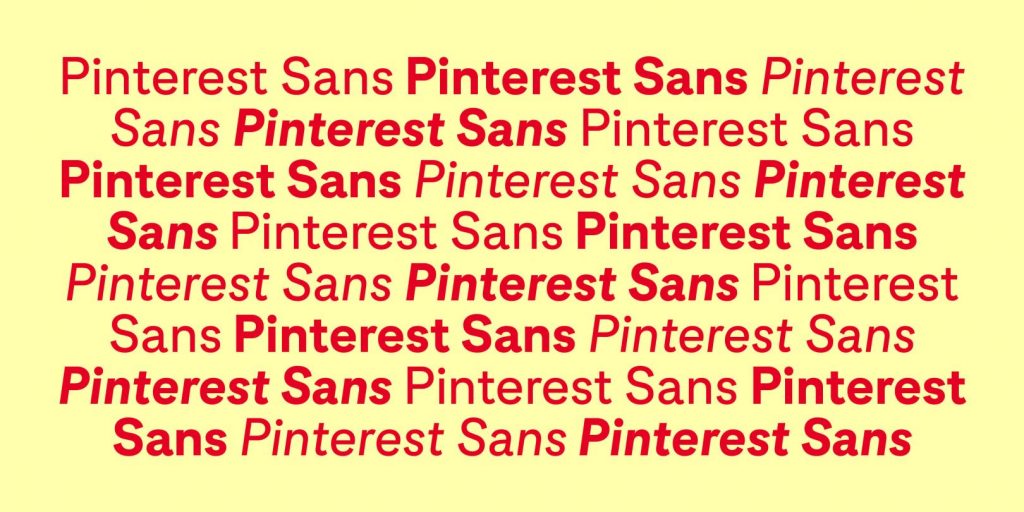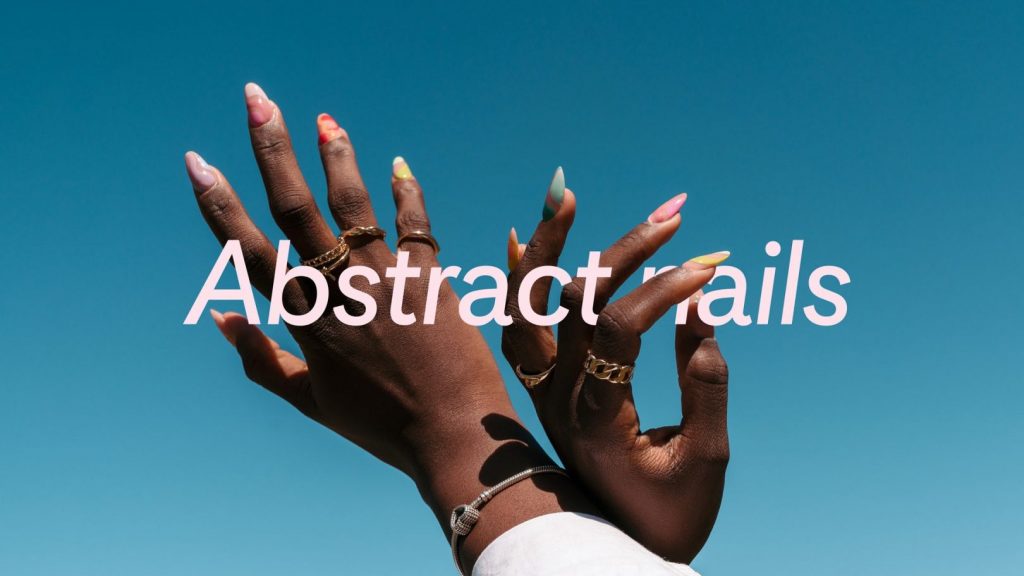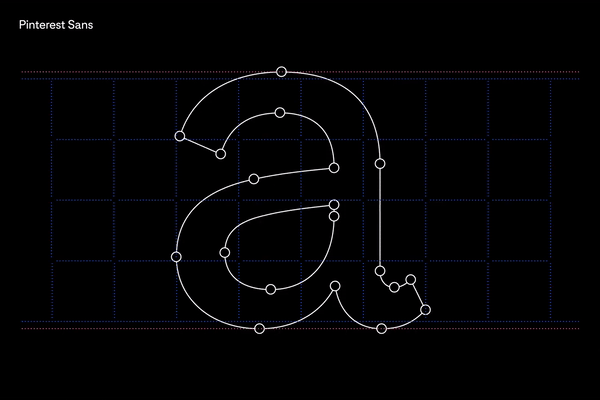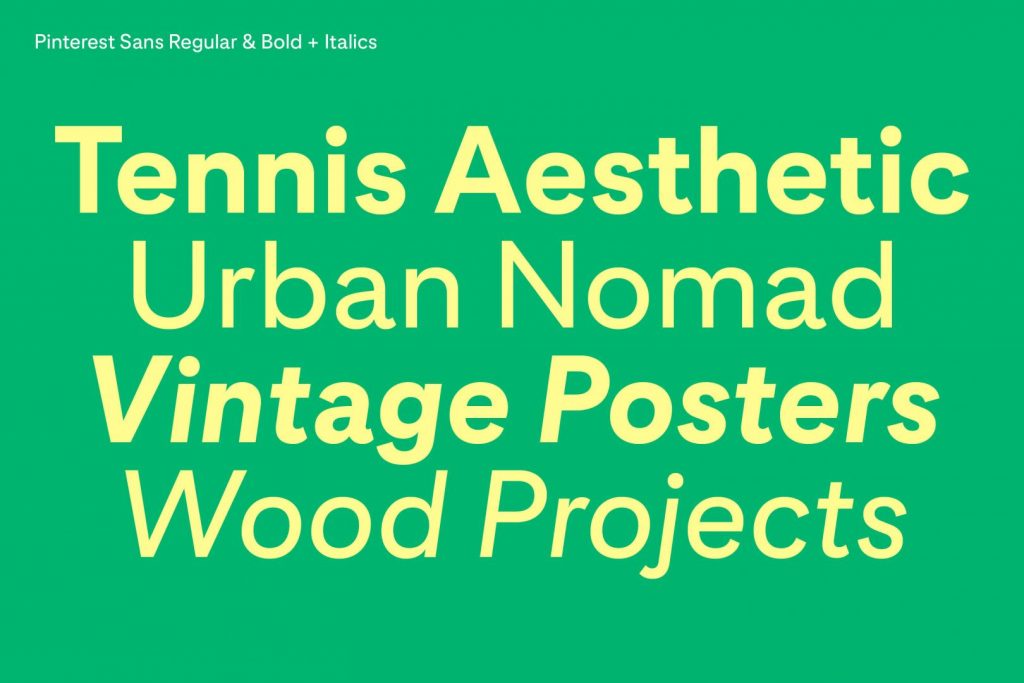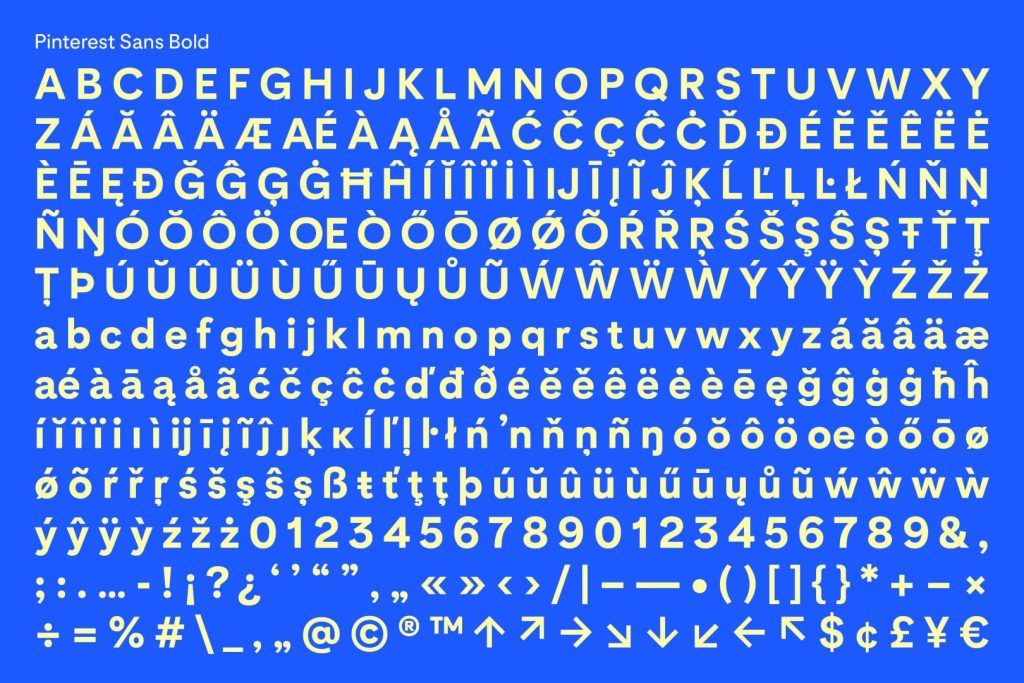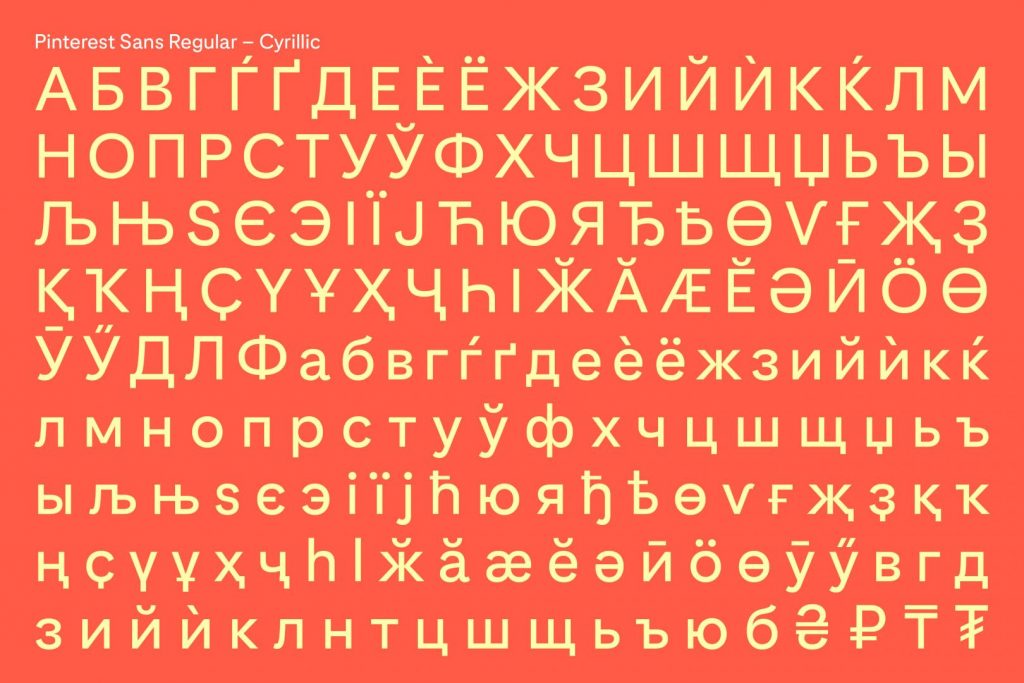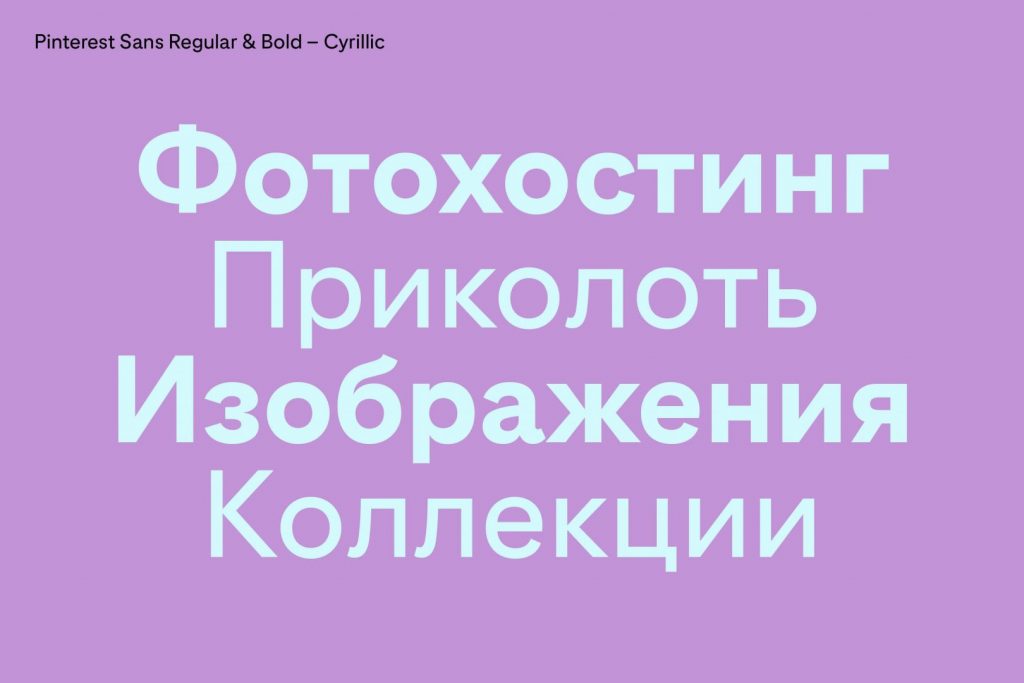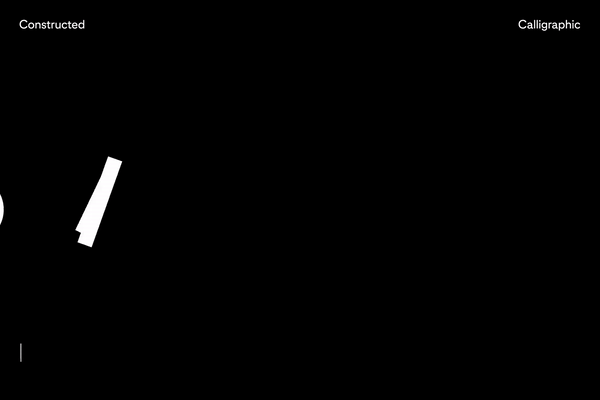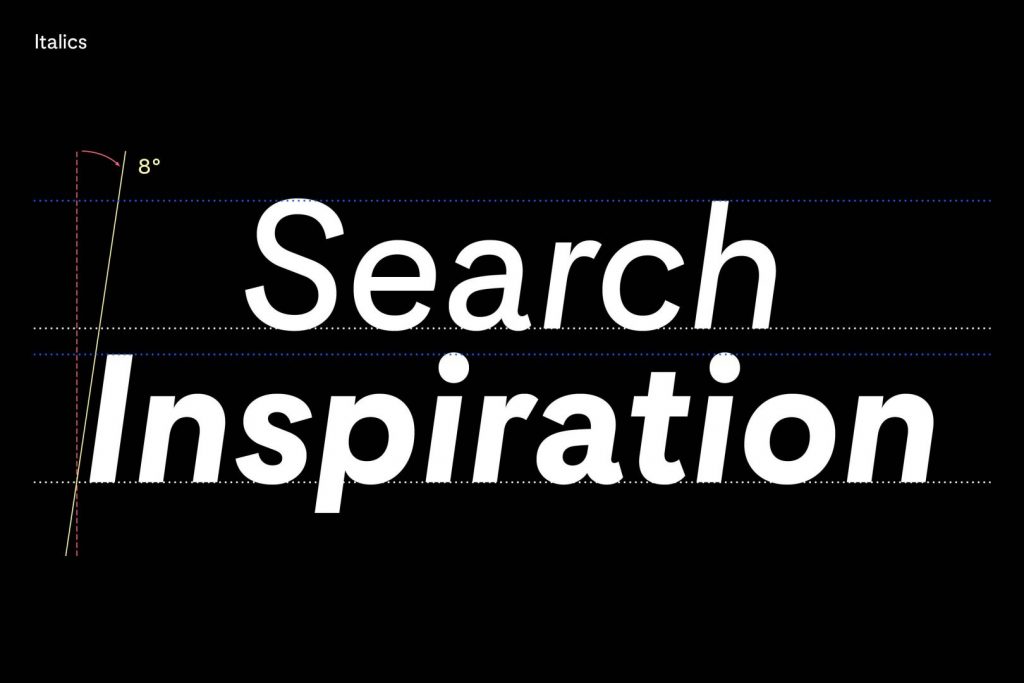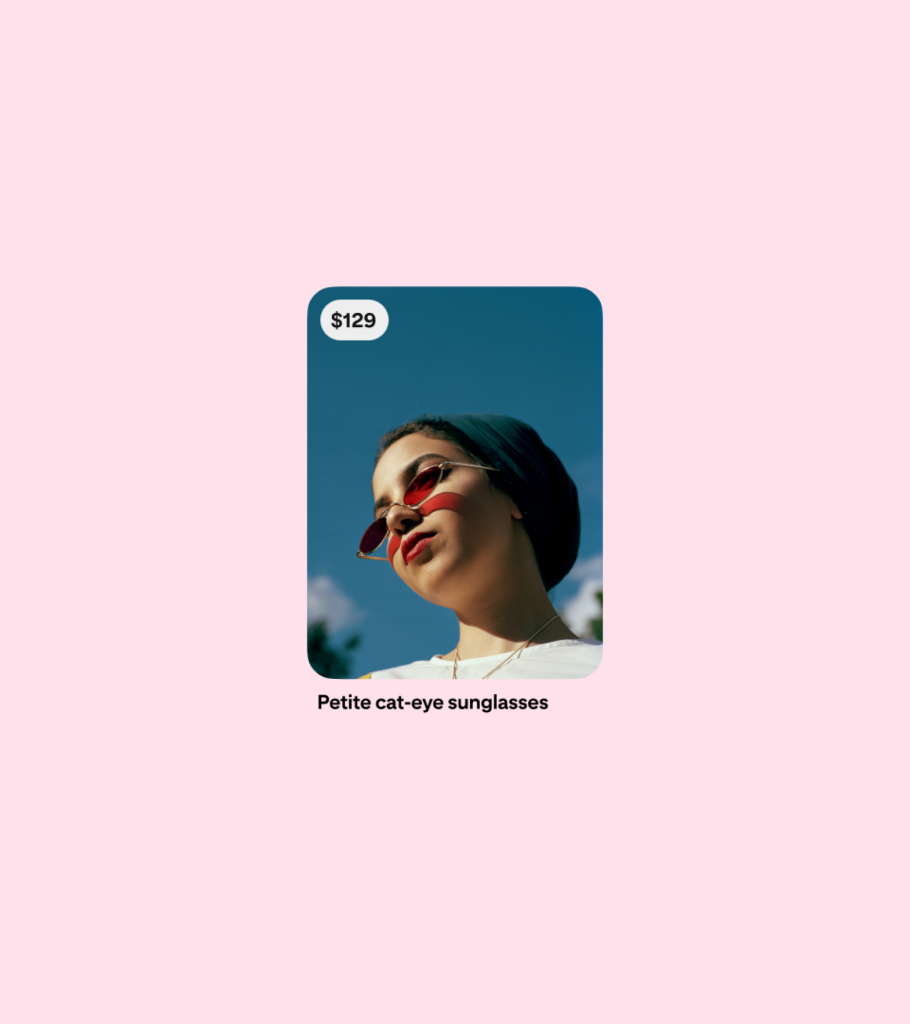
Xưởng thiết kế kiểu chữ nổi tiếng Grilli Type của Thụy Sỹ vừa kết hợp với Pinterest để cho ra đời typeface của bộ font chữ Pinterest Sans, trong kế hoạch hợp nhất thương hiệu trực quan của mạng xã hội hình ảnh này.
Ngoài việc tạo ra Pinterest Sans và Pinterest UI để tăng khả năng đọc cũng như số lượng phong cách riêng của hãng, dự án còn mở rộng để hỗ trợ các kiểu gõ Cyrillic, Hy Lạp, Việt Nam và Nhật Bản.
Trong showcase giới thiệu quá trình thực hiện, Grilli Type cho thấy sự tỉ mỉ đến từng chi tiết một cách đáng kinh ngạc. Pinterest Sans có những chi tiết nhỏ cho thấy nguồn cảm hứng của nó trong các kiểu chữ sans serif hình học và thư pháp, với mục tiêu tạo ra một kiểu chữ đặc biệt dễ nhận diện vượt qua ranh giới giữa ký tự và độ dễ đọc.
Để đạt được điều đó, Pinterest Sans là sự kết hợp hoàn hảo giữa tính mỹ thuật và chức năng. Sạch sẽ, gọn gàng những vẫn đầy tính cách, Pinterest Sans mang đến sự thoải mái và dễ dàng khi dùng đồng thời toát lên sự quen thuộc như thể chúng ta đã biết về kiểu chữ này từ lâu rồi.
“Chúng tôi không nghĩ rằng sự quyến rũ và chức năng nên loại trừ lẫn nhau”, Noël Leu, đồng sáng lập của Grilli Type chia sẻ, “trên thực tế, hai khía cạnh này được liên kết chặt chẽ với nhau.” Với mục tiêu các kiểu chữ phải dễ đọc và biểu cảm để truyền tải thông điệp, Noël cho biết đội ngũ ở Grilli Type phải trò chuyện liên tục và kéo dài với các quyết định và kết luận được rút ra thông qua các thay đổi thiết kế “vi mô và vĩ mô”.
Mối quan hệ đối tác sáng tạo dựa trên cơ sở trao đổi và thấu hiểu lẫn nhau có ý nghĩa vô cùng quan trọng đối với Grilli Type. “Chúng tôi thường đặt nặng vấn đề cá nhân cho dù đó là một đội thể thao hay một kiểu chữ,” Noël giải thích, trả lời về kiểu chữ yêu thích của mình.
“Chúng tôi xem chúng như một nhóm gồm các ký tự chỉ hoạt động chung với các ký tự khác cùng thể loại. Nếu chọn ra một ký tự duy nhất, cấu trúc riêng lẻ của nó không có gì nổi bật”. Noël chia sẻ: “Điều làm cho Pinterest Sans trở nên đặc biệt là sự kết hợp giữa hình học chức năng và nét chấm phá của con người.” Sự ấm áp và tích cách của từng ký tự cũng được đội ngũ Grilli Type lưu tâm trong quá trình thiết kế.
“Công việc của chúng tôi không chỉ là nhà thiết kế mà còn là người trung gian giữa việc nhận diện thương hiệu và biểu đạt kiểu chữ,” Noël nói, giải thích về quá trình hợp tác chặt chẽ với Pinterest để đưa ra chiến lược, quyết định chức năng và thẩm mỹ mục tiêu cho kiểu chữ này.